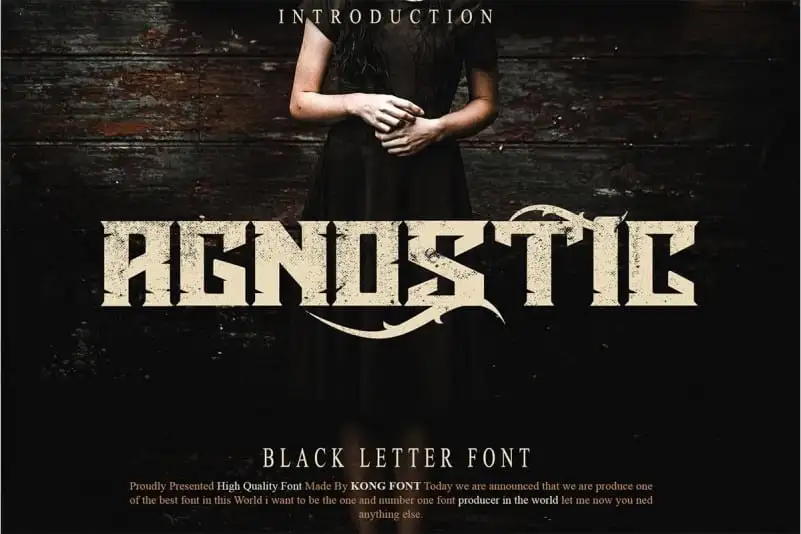
Agnostic Display Font é uma tipografia inspirada na arte vintage das placas e letras, com um toque elegante e artístico. Esta fonte vem equipada com letras maiúsculas especiais e alguns caracteres alternativos para criar um visual sofisticado e criativo em seu design. Ela se destaca perfeitamente tanto para criações de logomarca quanto para headlines ou frases curtas, oferecendo uma versatilidade ótima que a torna ideal para diversos tipos de aplicação gráfica. Além disso, o produto inclui um conjunto de ornamentos vetoriais e logomarcas. Este acréscimo é uma ótima adição, pois permite aos criativos personalizar ainda mais seu design, fazendo com que cada projeto seja único e destacado. Se você está em busca de uma fonte capaz de dar vida a suas criações de maneira elegante e sofisticada, Agnostic Display Font pode ser sua escolha perfeita.